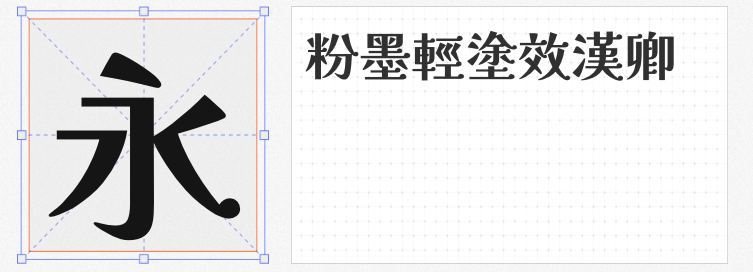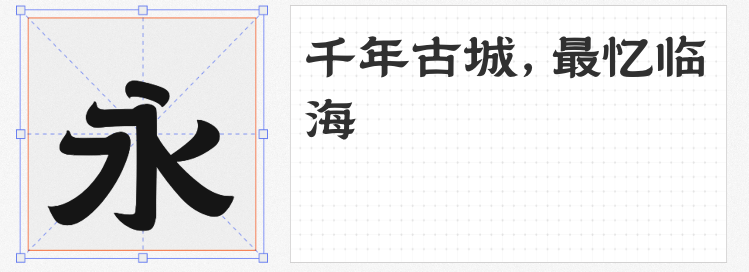
端午佳节将至,设计海报、包装或文化物料时,选择一款兼具传统韵味与现代创意的字体至关重要。以下四款免费商用字体,既能体现端午文化底蕴,又能为作品注入独特视觉张力。
1. 阿里妈妈刀隶体
以《爨宝子碑》为灵感,这款字体融合隶书与楷书特征,笔触锋利如刀,横画“雁尾”收笔方硬,折弯处棱角分明,传递出朴拙倔强的气质。其结构打破常规匀称,单字大小对比强烈,如“永”字可占“人”字两倍空间,却通过中轴线统一形成险中求正的韵律。端午设计中,可用于龙舟竞渡、粽叶飘香等主题的标题,凸显节日的热烈与历史的厚重感。
2. 临海隶书
由临海市社发集团与乡立方字体团队联合打造,这款字体以隶书为骨架,笔画宽厚稳重,融入临海古城墙纹样、千佛塔碑刻等文化符号,字形中暗藏城市记忆。其古拙的古典美感与端午的民俗气息相得益彰,适合用于粽子礼盒包装、龙舟赛事海报,传递文化传承的厚重感。
3. 宇文天穹
基于日本“解星计划”开发的开源字体,参照传承字形标准化文件修改为中文传统字形,横细竖粗,横笔末端的小圆形如星空点缀,兼具明体的端庄与圆体的柔和。繁体设计更显雅致,适合端午诗词、传统习俗介绍的排版,为文字增添一份诗意与宇宙的遐想。
4. Aa厚底黑
以窄长字形与弧度曲线为特色,笔画粗壮如黑体,却因底部的加厚设计而更具活泼感。其现代风格适合端午主题的年轻化设计,如龙舟电竞比赛海报、粽子IP形象周边,用粗犷的线条传递节日的活力与趣味。